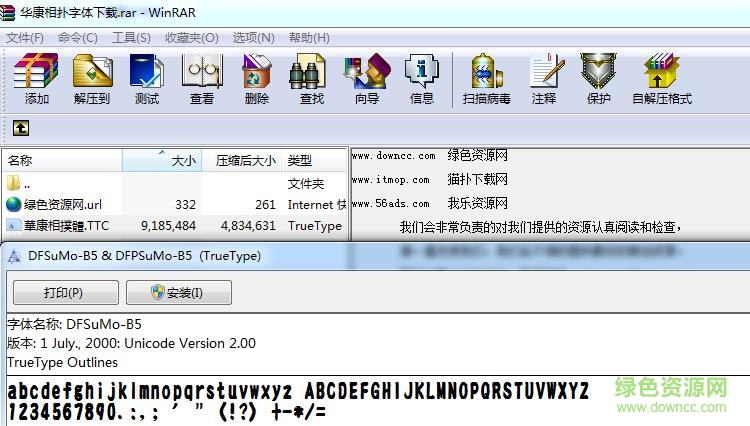
華康相撲體字體
華康相撲體字體是一款能夠運(yùn)用到眾多字體模板中廣泛使用的字體文件,為你實(shí)現(xiàn)工業(yè)設(shè)計(jì),包裝設(shè)計(jì)以及藝術(shù)設(shè)置,工作編輯當(dāng)中,擁有十分廣泛的使用效果,受到眾多用戶的喜愛,是一款常見的字體樣式!